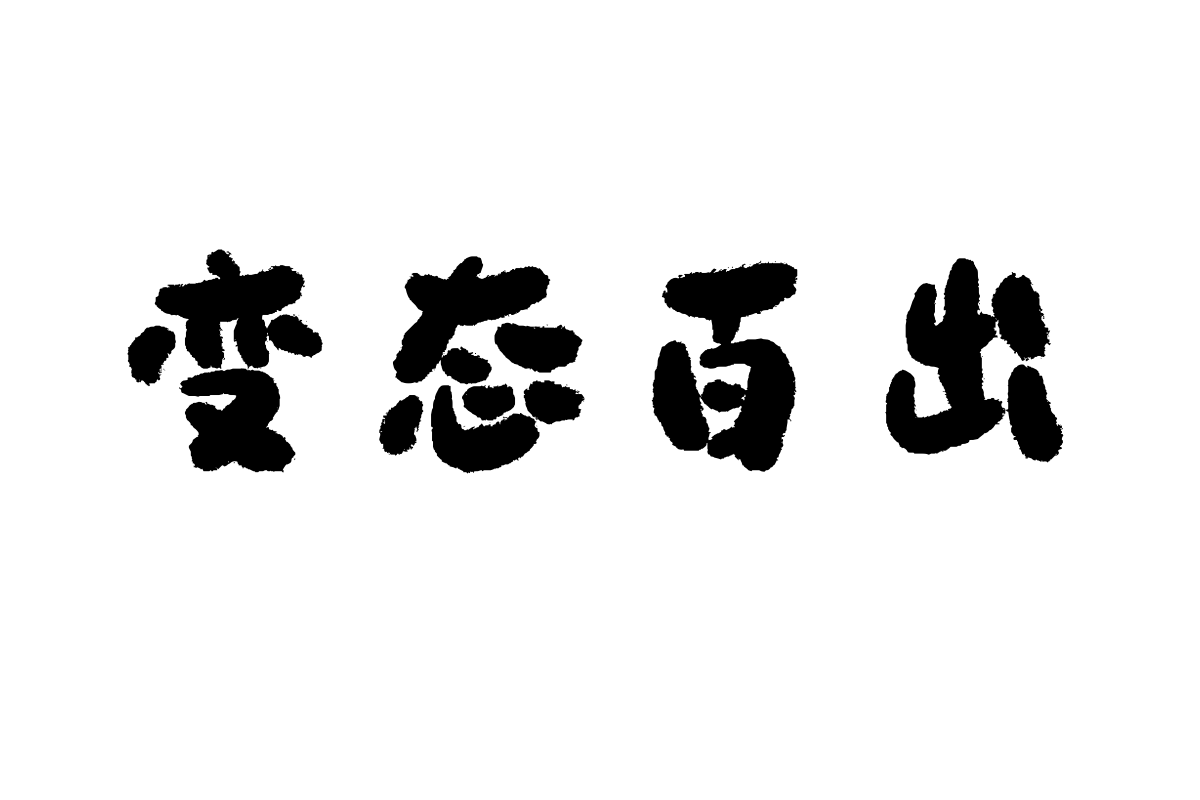
三极初墨体是一种具有独特风格的汉字字体,它的设计灵感来源于传统的书法艺术。这种字体的特点是笔触流畅自然,线条粗细变化丰富,既有刚劲有力的笔画,也有柔和细腻的线条。
三极初墨体的笔画结构严谨,每个字的构造都经过精心设计,力求达到平衡和谐的效果。这种字体适用于需要展现传统文化韵味和艺术感的场合,如书籍、杂志、广告等。
总的来说,三极初墨体是一种充满个性和艺术气息的汉字字体,它能够为作品增添独特的视觉美感和文化底蕴。